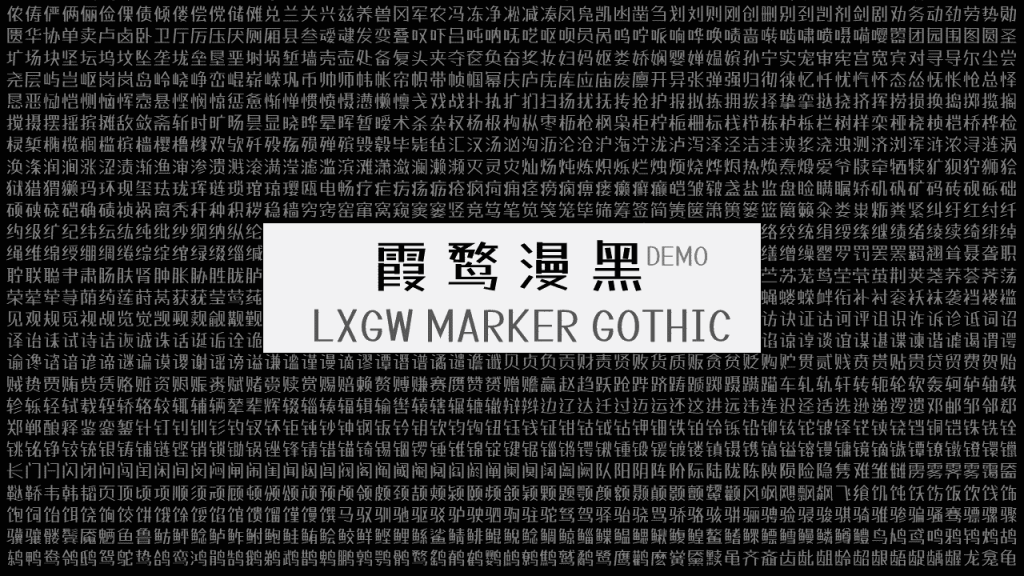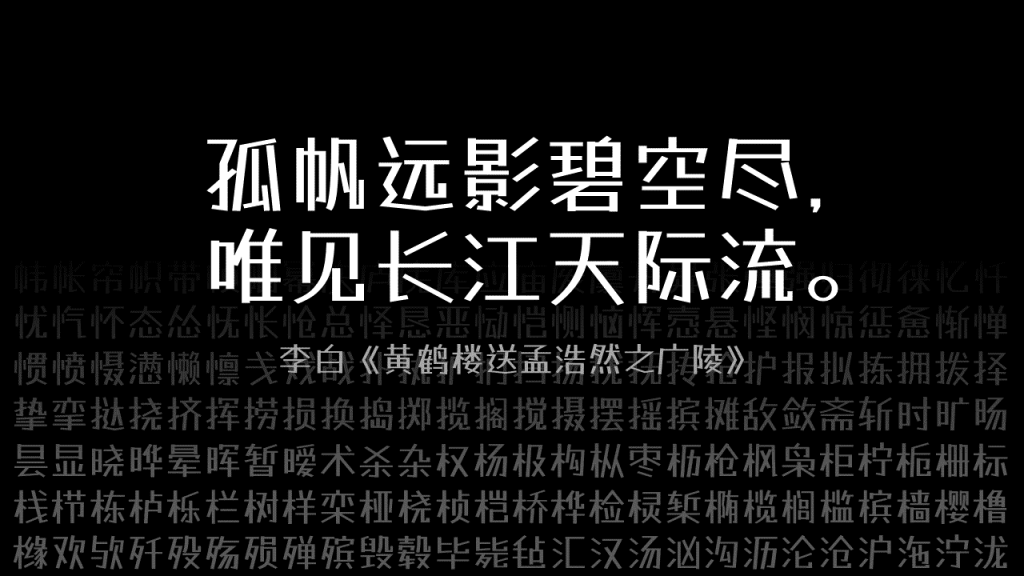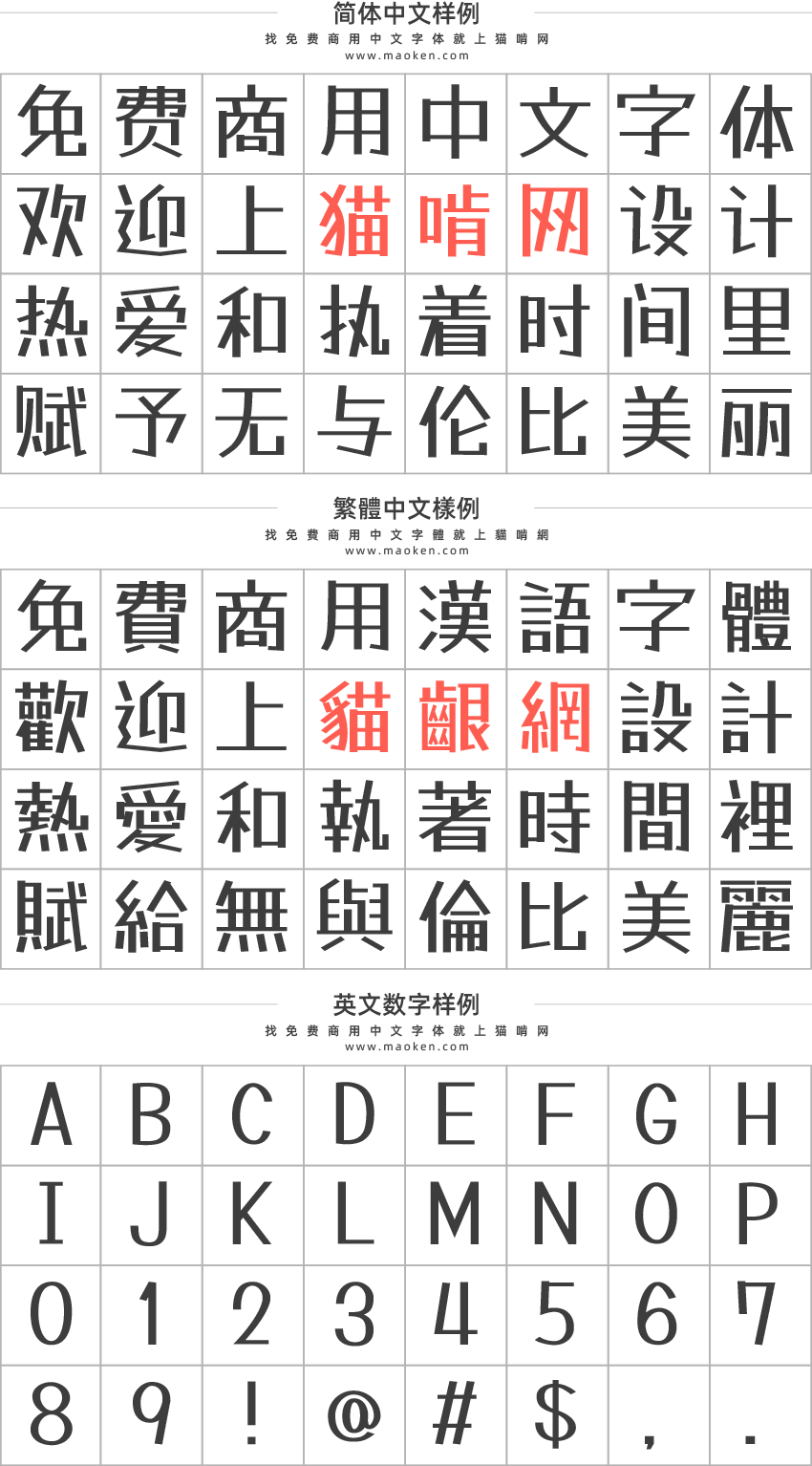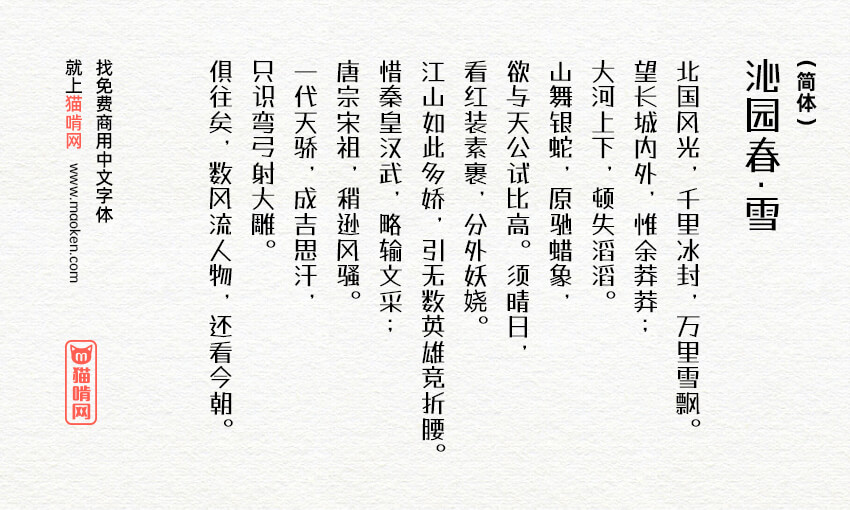
| 字体作者:落霞孤鹜 (中国大陆) | 字体字重:1个 |
霞鹜漫黑是一款由 Tanugo手写体衍生的开源中文字体。本字体是基于 たぬゴ角 改造的具有马克笔书写风格的中文字体,可用于漫画、广告等用途。
补字计划
简体部分
- 补完原字库中含有的繁体字对应的简化字;
- 补完 3500 常用汉字 ①;
- 目标字汇范围内修改 G 形;
- 补完 GB/T 2312-1980(原文)及《通用规范汉字表》(原文)二级字。
① 包括「现代汉语常用字表」(老 3500 字)及「义务教育语文课程常用字表」(新 3500 字,等效于《通用规范汉字表》一级字表),共计 3603 字。
繁体部分
- GB/T 12345-1990(原文)6866 个汉字;
- 台湾地区「常用国字标准字体表」4808 个繁体常用汉字;
- 香港地区「常用字字形表」 常用汉字及部分异体字;
- BIG5 一级(常用)汉字 5401 个;
- 《通用规范汉字表》附件 1:「规范字与繁体字、异体字对照表」中的繁体字列(一、二级)。
目前本字体包含共计 1.1 万余字,可基本满足简繁日常用字的显示需要。
Ver 1.003(2025/09/12)
- 新增 Unicode 17.0 引入的儿化音标记「儿
U+16FF2」「兒U+16FF3」。
Ver 1.002(2025/09/08)
- 新增特殊符号:
U+FFFC。
Ver 0.310(2024/09/08)
- 补全「通用规范汉字表」「现代汉语通用字表」所收字及对应繁体。详情点此查看。
- 调整字形:僇塳媱寧揳楔硿纜虧鏖雊麈麋麑麖麝龀
Ver 0.300(2023/08/22)
- 新增千余汉字,以及其他符号,详情点此查看。目前本字体已包含 IICore 所有汉字。
- 调整字形:判埓柿泜淏贼。
- 新增令和合字「㋿」。
Ver 0.200(2023/07/05)
- 新增 893 个汉字(繁体为主),详情点此查看。
- 调整字形:症
- 新增以下符号:㉛㉜㉝㉞㉟㊱㊲㊳㊴㊵㊶㊷㊸㊹㊺㊻㊼㊽㊾㊿
Ver 0.108(2023/03/07)
- 新增汉字:㮾娭毑啟汮
- 调整字形:咲嗹掷撻朕樋渕漣燵祿禝禪禮禰禳联膸謎迚迯送逎逕這逹遉遙遜遞遡遯遲遶邁邇邉邊邏郑釮鎚鎮鎰鎹鏈鑓隨韃韆﨤
- 调整和新增其他符号,详情点此查看。
Ver 0.107(2023/02/27)
- 调整以下字形:炒蚕蜃唇
Ver 0.106(2023/02/25)
- 调整以下字符:⇋⇌
Ver 0.105(2023/02/24)
- 调整以下字形:嘆漢謹遷選難頻類顧飽
- 新增以下字符:ḴḵḺḻẚẜẝ̮̯̰⁰⁵⁶⁷⁸⁹⁺⁻₀₁₂₃₄₅₆₇₈₉₊₋‱‴‶‷‛‟‼⁈⁉⁝⅐⅑⅒⅓⅔⅕⅖⅗⅘⅙⅚⅛⅜⅝⅞⅟↉⇋⇌⇍⇎⇏⇐∅∆∉∌∣∤∦≓≜∭∯∰∼〡〢〣〤〥〦〧〨〩㉑㉒㉓㉔㉕㉖㉗㉘㉙㉚㊀㊁㊂㊃㊄㊅㊆㊇㊈㊉⇑⇓ゕ゠ヷヸヹヺゖㄪㄫㄬㄭㄮ
Ver 0.104(2023/02/20)
- 增补部分扩展拉丁字母及音标(感谢 Des-Magmeta 的协助)。
Ver 0.103(2023/02/18)
- 调整以下字形:慨绣
- 调整以下字形:害辈连
- 调整蝌蚪引号:
“‘’” - 新增以下汉字:𩽾𩾌
Ver 0.101(2023/02/16)
- 调整以下字形:汤羡邹
Ver 0.100 (2023/02/14)
- 优化希腊字母和西里尔字母(Georgome);
- 调整 GB/T 2312-1980 及通规表范围内原始开源字体(Tanugo)所收字的字形,使其接近 G 形;
- 补全 GB/T 2312-1980、通用规范汉字表一二级汉字;
- 补全 GB/T 2312-1980 所收录的其他字符(拼音字母、注音符号、运算符、制表符等)。
Ver 0.003 (2021/05/04)
- 修复「类」显示为「娄」的问题。
Ver 0.002 (2021/01/30)
- 新增 204 个汉字; 点此查看
- 修复「霉」显示成「雾」的问题。
Ver 0.001 (2021/01/26)
- 霞鹜漫黑Demo版正式发布
示例图建议更新一下,0.105版本的“漢”改了
这个字体的最新版好多字都改字形了,这示例图还是没有更新,还是旧版字形
喜歡,期待更多補充,比如:繁體的“說”字“囉”字缺了
真的很喜欢这一款,用在手机上很好看,期待补完
类字打出来是娄字
0.003 版本已修复。
咿 字显示黑块?号
喵星人想有 喵 字:D
希望後續可能會有更多的字
我随手补了一下,并且居中了一下(原字体有些字间距不一),传到了https://github.com/AlexanderMisel/font-test/blob/gh-pages/LXGWMarkerGothic.ttf 。你可以看下这个效果。
正在补一些常用的字
已更新0.002版本,有喵字了